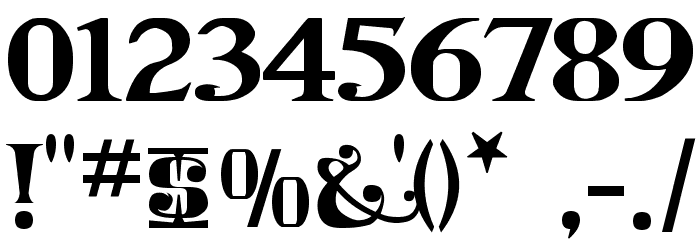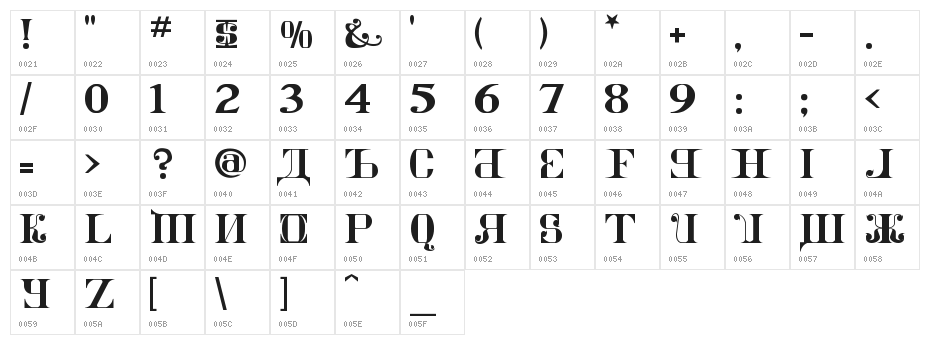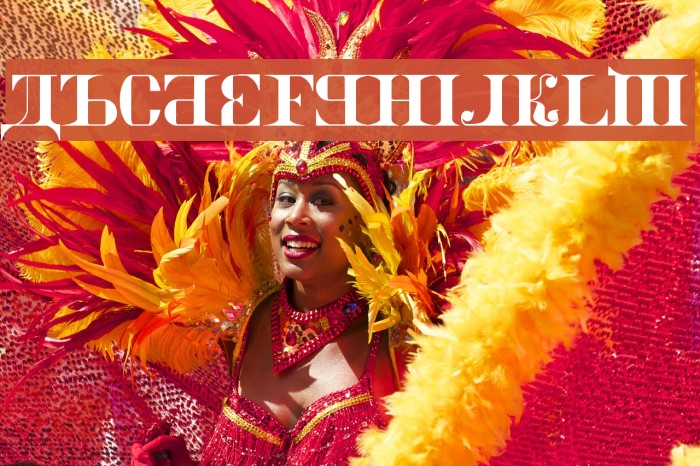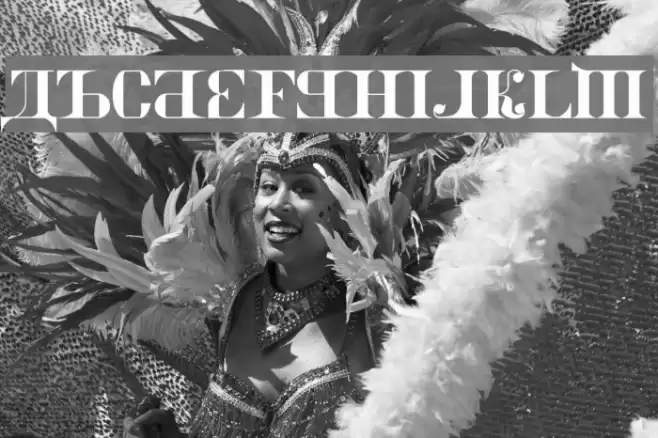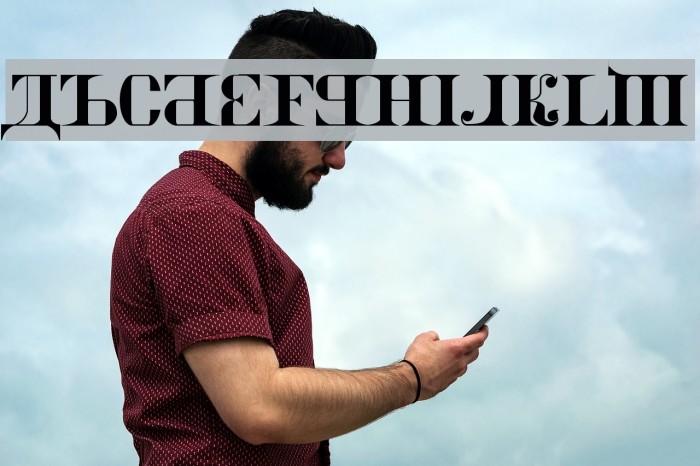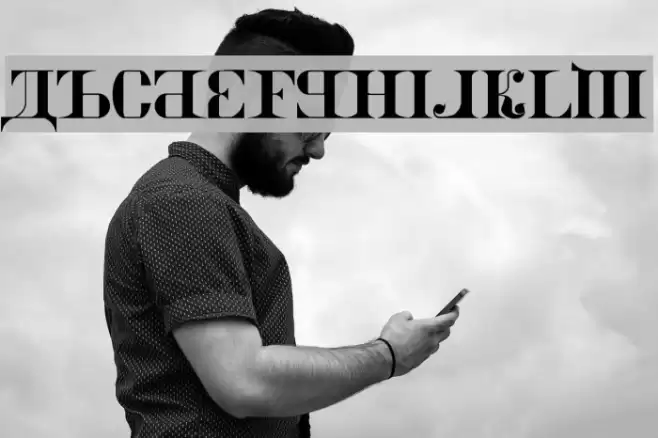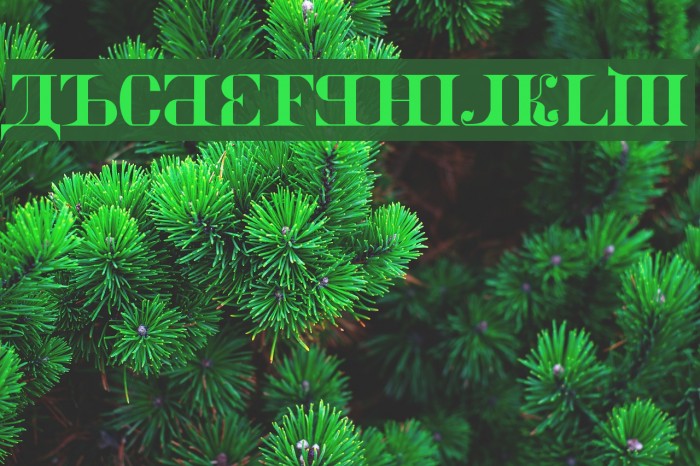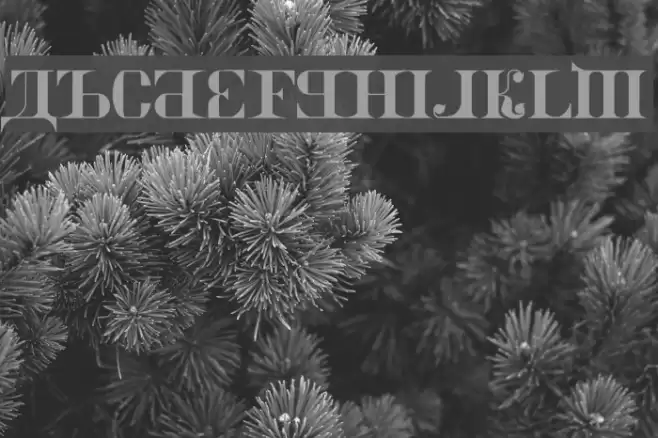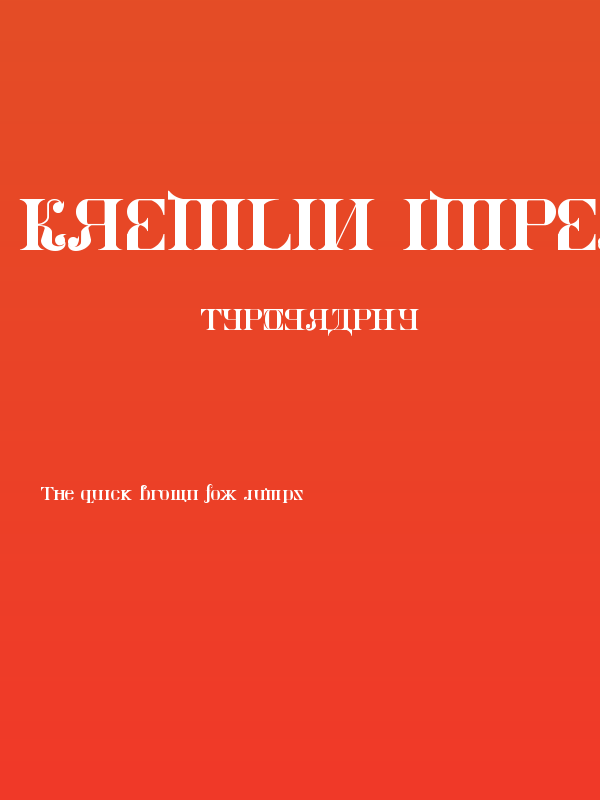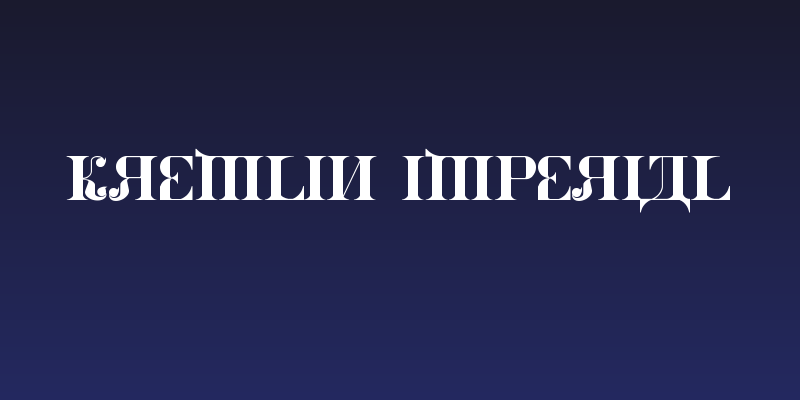
Kremlin Imperial Font
✎ Thick
| Vorgeschlagene Projekte | Ideal for projects requiring a strong, authoritative presence such as headlines, posters, branding, and editorial design. |